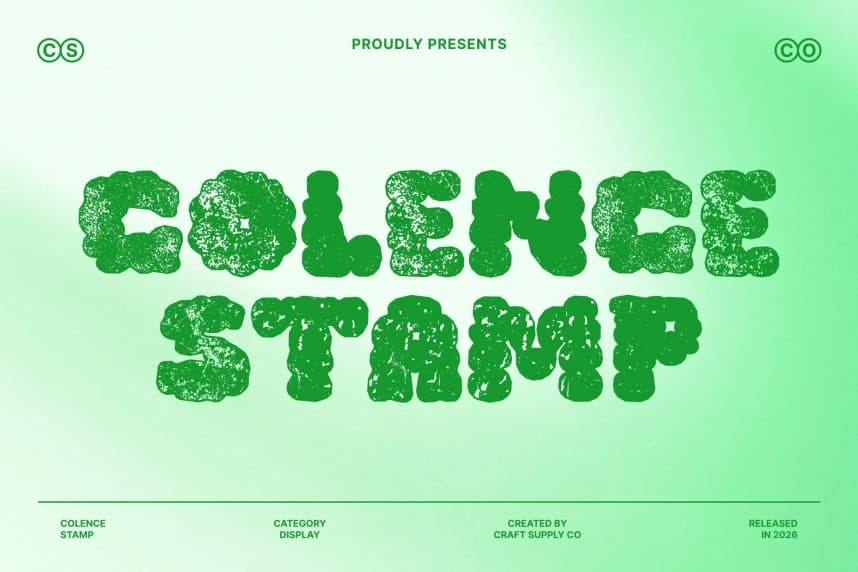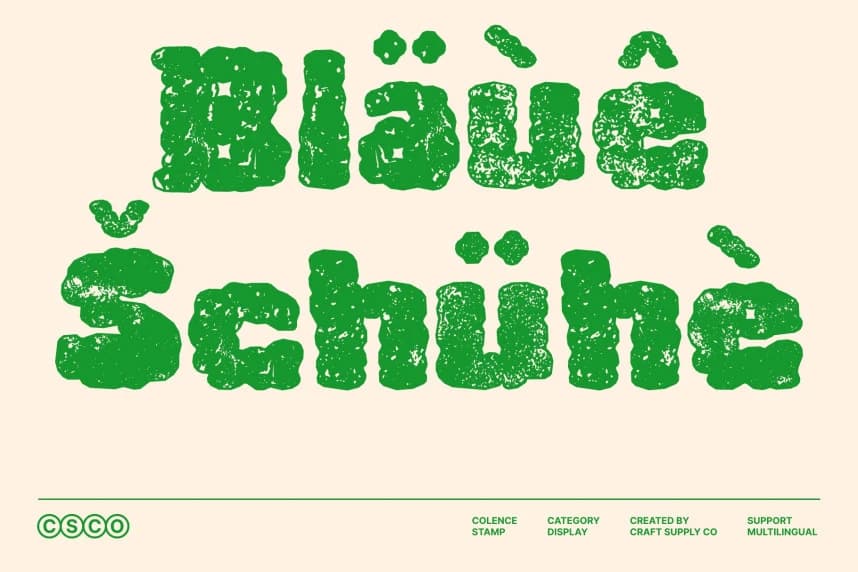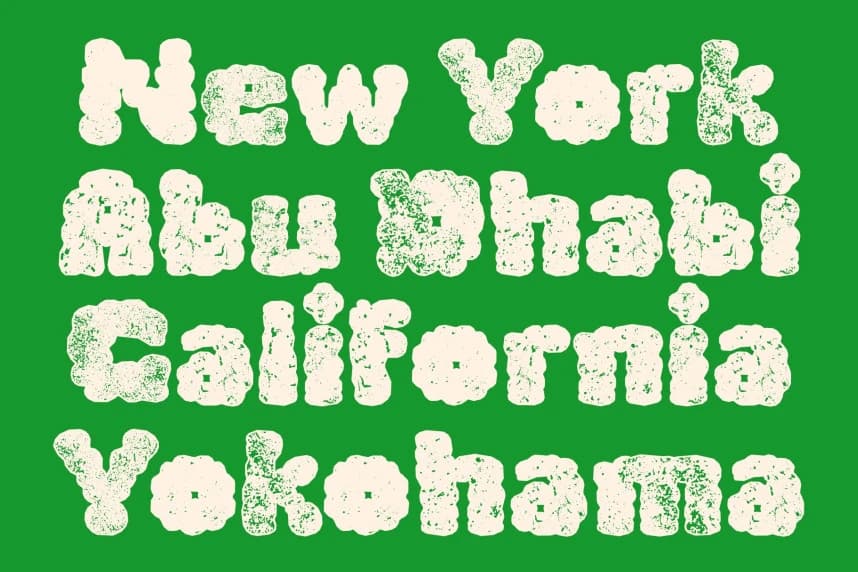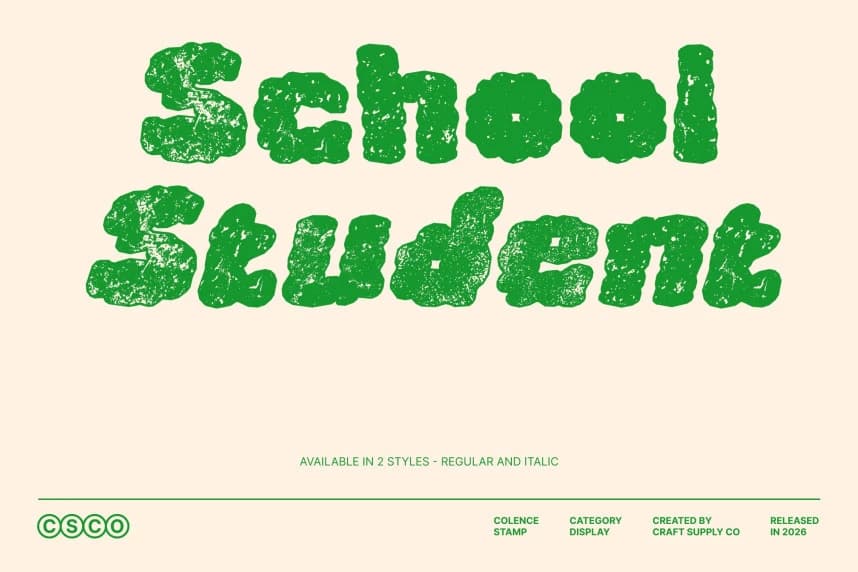
Colence Stamp font
Colence Stamp Font – Bulut benzeri neşeyi vintage dokuyla buluşturuyor; Baskılı Karakter ile oyunlu bulut ilhamı. Bu, kabarık bulutların neşeli güzelliğini yakalıyor ve ince bir baskı dokusuyla bunu zenginleştiriyor.
Colence Stamp Font – Bulut benzeri neşeyi vintage dokuyla bir araya getiriyor. Damgalı karakterlerle oyunbaz bulut ilhamı. Bu, kabarık bulutların neşeli güzelliğini yakalıyor ve ince bir damgalı doku ile ona zenginlik katıyor.
Colence Stamp